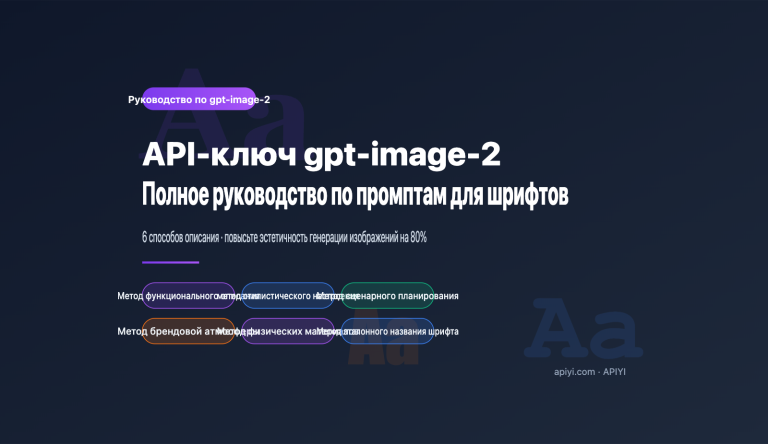
Полное руководство по промптам для шрифтов в API gpt-image-2: 6 способов описания, повышающих эстетичность генерации изображений на 80%
Многие пользователи, работающие с API gpt-image-2 или генератором изображений в ChatGPT, сталкиваются с одной и той же проблемой: текст на картинках распознается отлично, но шрифты всегда выглядят как «инженерный стандарт» — простейший гротеск без засечек, лишенный брендинга и дизайнерского лоска. Эта «аскетичная эстетика» особенно бросается в глаза при создании постеров, обложек для соцсетей или рекламных…